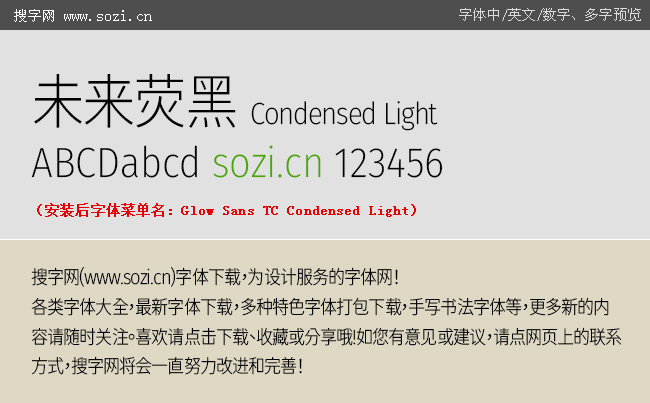
未來熒黑GlowSansTC-Condensed-Light
搜字網(wǎng)給大家提供一款未來熒黑GlowSansTC-Condensed-Light中文字體下載,未來熒黑GlowSansTC-Condensed版是未來熒黑中的一個(gè)瘦長體系列,未來熒黑是一個(gè)基于思源黑體、Fira Sans和Raleway的開源字體項(xiàng)目,該字體由八種字重,字體中宮與字面更加收斂,細(xì)節(jié)上面處理更加的干練,適合應(yīng)用于藝術(shù)設(shè)計(jì)、平面宣傳設(shè)計(jì)、網(wǎng)頁設(shè)計(jì)等廣告設(shè)計(jì)。